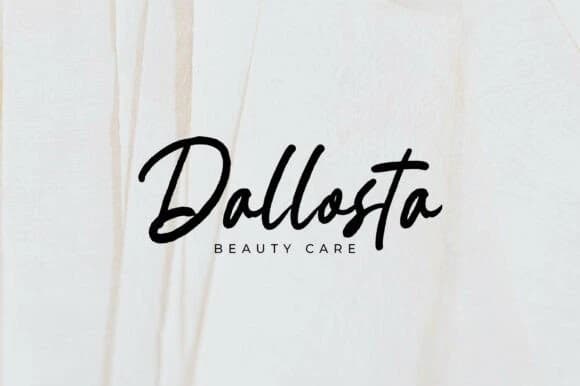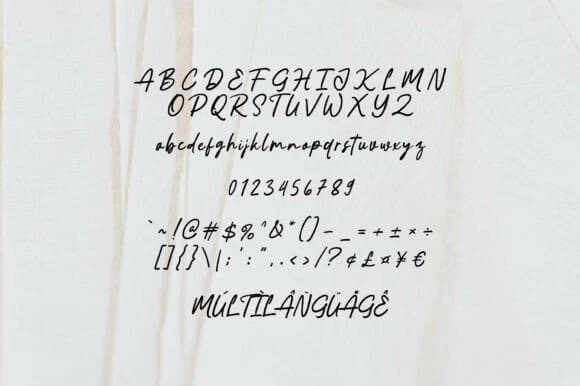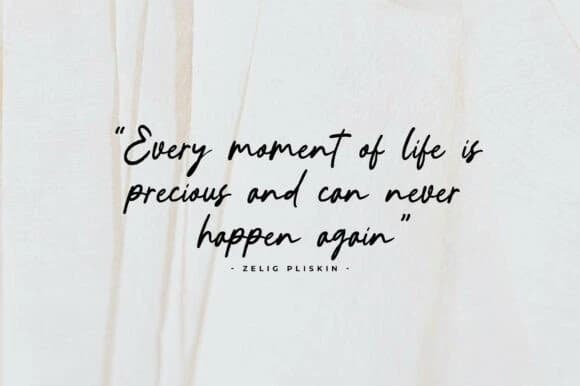
Shareit Script Font
Shareit Script Font, posterler, logolar, dergiler, kapaklar, afişler ve daha pek çok şey için mükemmel, modern ve sevimli bir el yazısı fontudur! Bu harika fontu edinin ve güzel tasarımlar yaratmak için kullanın. İnanılmaz derecede geniş bir proje yelpazesine kolayca uyum sağlar.
Shareit Script Font, posterler, logolar, dergiler, kitap kapakları, afişler ve çok daha fazlası için mükemmel olan modern ve sevimli bir el yazısı yazı tipidir! Bu harika fontu edinin ve güzel tasarımlar yaratmak için kullanın. Bu, inanılmaz derecede geniş bir proje yelpazesine kolayca uyum sağlar.